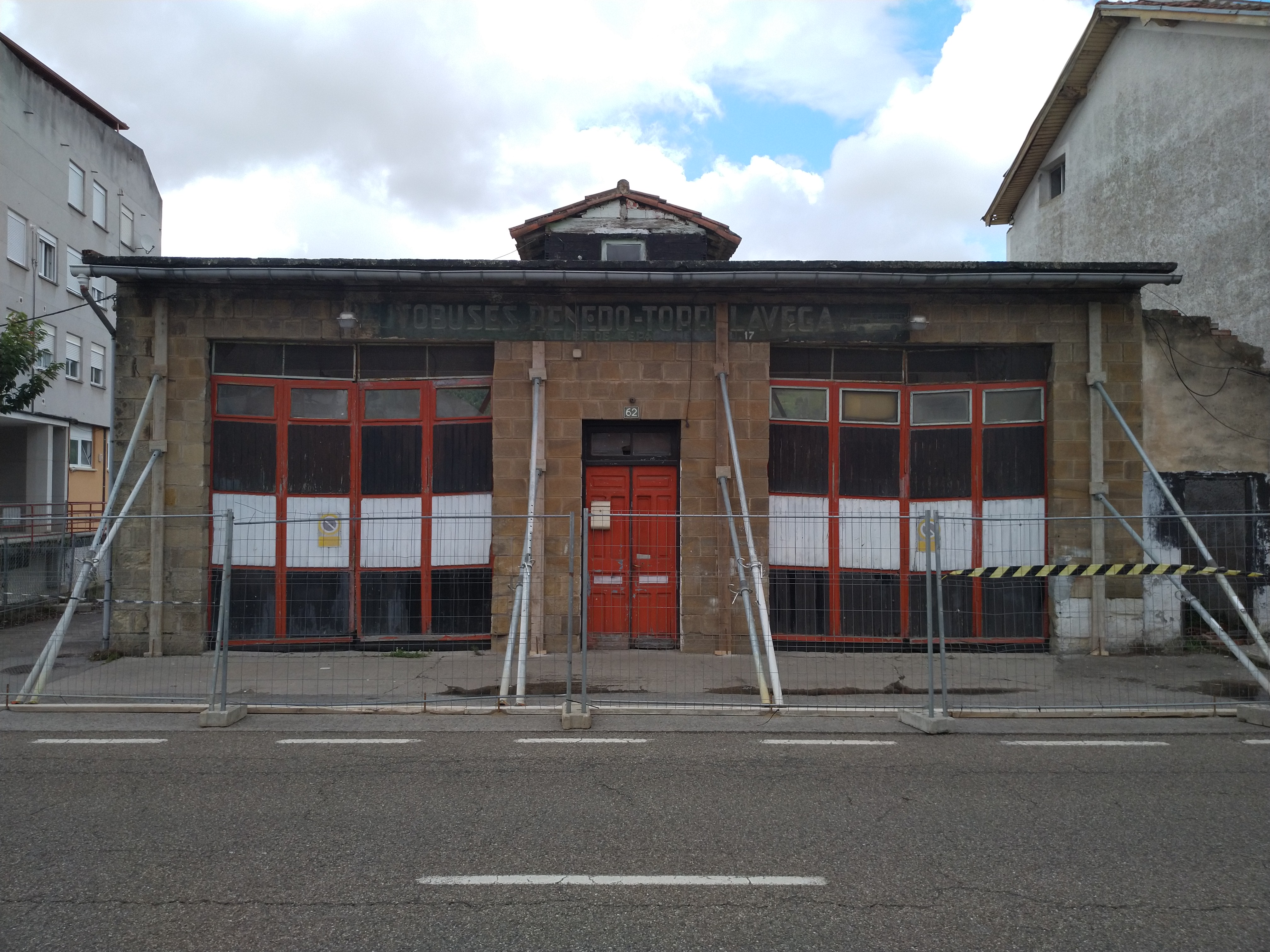
Autobuses Renedo Torrelavega
Tras el rescate de Coterón, en Renedo, vimos como desaparecía definitivamente el taller de «Autobuses Aranda Calderón«. Un taller fundado en los años 50 que conservaba su rótulo pintado sobre el dintel y la piedra.
Desde Santatipo hemos recuperado esas letras para su recuerdo.